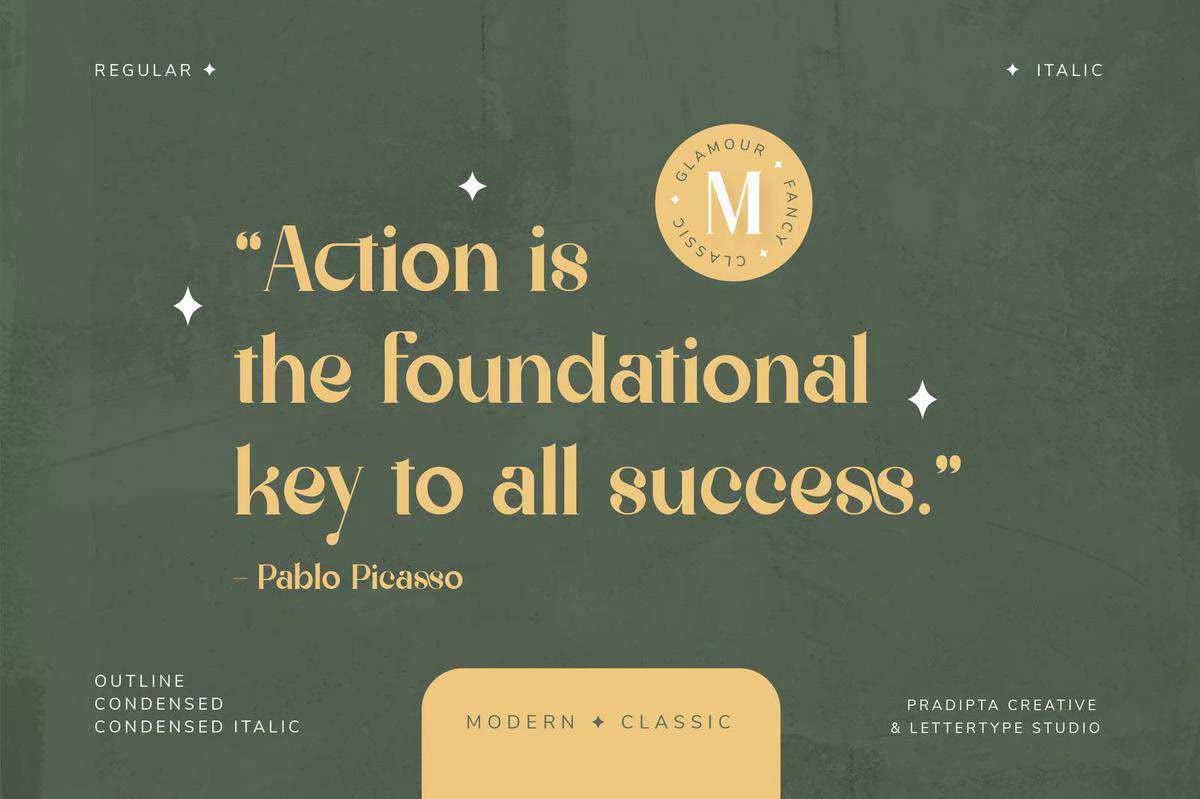
Milestoneserif是一款经典、迷人、时尚的香水。这款香水将完美地应用于您的标志设计、品牌推广、服装、标牌、标题、海报、婚礼宣传等等!我创建该字体的目标是创建一个具有现代风格和古典风格的出色作品,这将有助于您的项目更好、更出色。我相信每一个细节的形状和细节都会为您带来完美的效果。不要错过!Milestoneserif是一款经典、迷人、时尚的香水。这款香水将完美地应用于您的标志设计、品牌推广、服装、标牌、标题、海报、婚礼宣传等等!我创建该字体的目标是创建一个具有现代风格和古典风格的出色作品,这将有助于您的项目更好、更出色。我相信每一个细节的形状和细节都会为您带来完美的效果。不要错过!